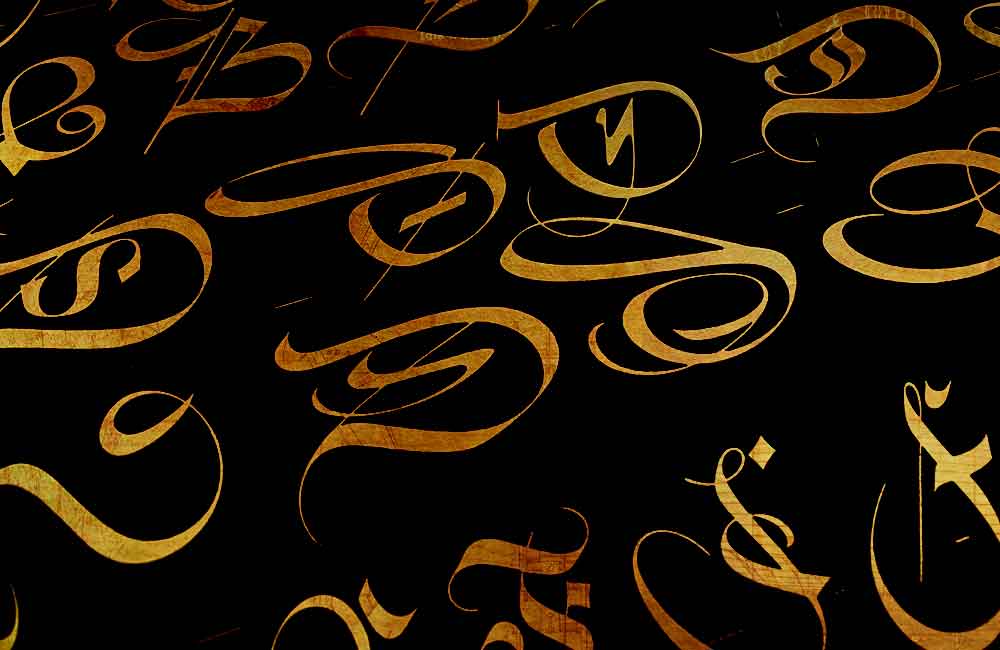
Kalligraphische Studien des Grafikdesigners, Typografen und Kalligraphen Friedrich Hermann Ernst Schneidler (1882–1956) zu den Initialen seiner Zentenar-Fraktur (1937–1939), anlässlich eines Wettbewerbs zum hundertjährigen Bestehen der Bauerschen Schriftgießerei in Frankfurt am Main. Interpretiertes Bildzitat (Ausschnitt) aus »Wo der Buchstabe das Wort führt« (Seite 201) von Prof. Kurt Weidemann.